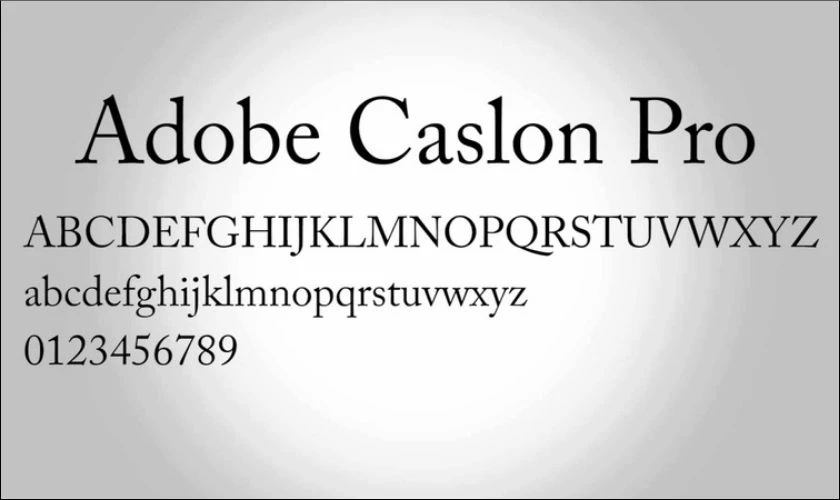
Font chữ La Mã (Roman Capitals) là nhóm phông chữ có chân (Serif) mang tính biểu tượng lịch sử lâu đời nhất trong nghệ thuật Typography, được lấy cảm hứng từ các bản khắc chữ trên đài kỷ niệm và bia đá của Đế chế La Mã cổ đại. Với cấu trúc chữ in hoa uy nghi, các chân chữ sắc sảo và tỷ lệ kiến trúc chuẩn mực, nhóm phông chữ này toát lên vẻ đẹp quyền lực, trang trọng và trường tồn với thời gian. Doozypack.vn cung cấp link tải trọn bộ font chữ La Mã đẹp đã được Việt hóa chuẩn kỹ thuật, giúp bạn sở hữu kho phông chữ cổ điển này để thiết kế bao bì, nhãn rượu và bộ nhận diện thương hiệu cao cấp mà không lo lỗi hiển thị dấu thanh.
Đặc điểm thẩm mỹ độc đáo của bộ font chữ La Mã
Font chữ La Mã không chạy theo các xu hướng thiết kế nhất thời; sức hút của nó nằm ở sự chuẩn xác mang tính toán học và tinh thần monumental (hoành tráng, uy nghi) của kiến trúc cổ đại.
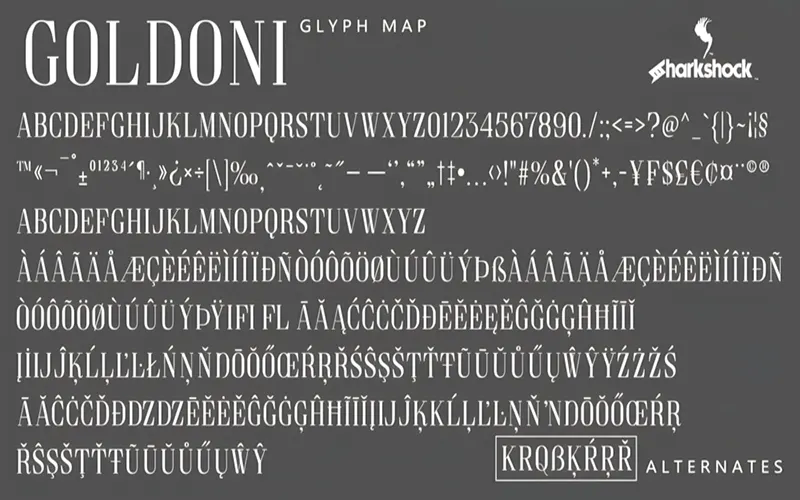
Phong cách Roman Capitals uy nghi mang âm hưởng đế chế cổ đại
Đặc trưng lớn nhất của phông chữ La Mã là hệ thống ký tự in hoa (All-caps) với tỷ lệ chiều rộng và chiều cao được tính toán dựa trên các hình khối hình học chuẩn mực. Các nét dọc sở hữu độ dày đĩnh đạc kết hợp cùng các nét ngang thanh thoát, tạo nên cảm giác vững chãi, uy quyền và minh bạch tuyệt đối. Khi đặt font La Mã làm tiêu đề trên bao bì, thương hiệu của bạn sẽ ngay lập tức khẳng định được vị thế di sản, sự uy tín lâu năm và phẩm cấp thượng hạng.
Chân chữ sắc sảo với tỷ lệ kiến trúc chuẩn mực
Phần chân chữ (serif) của kiểu chữ La Mã được thiết kế rất sắc lẹm, có độ mở rộng vừa phải ở các điểm kết thúc nét. Chi tiết điêu khắc tinh xảo này giúp các dòng tiêu đề trên vỏ hộp giữ được sự thanh thoát, kiêu kỳ nhưng vẫn vô cùng chắc chắn, rất phù hợp với các sản phẩm quà tặng doanh nhân, hộp rượu vang lâu năm hoặc văn bằng chứng nhận cao cấp.
Các biến thể phổ biến: Từ chữ cái đến Font chữ số La Mã
Khi tìm kiếm các bộ phông chữ này, bạn sẽ bắt gặp hai nhóm ứng dụng chính rất được ưa chuộng trong thiết kế đồ họa:
- Font chữ số La Mã đẹp (Roman Numerals): Các ký tự số như I, II, III, IV, V, X, L, C, M được thiết kế theo đúng chuẩn kiến trúc La Mã, thường được dùng để đánh dấu các phiên bản giới hạn (Limited Edition), mốc thời gian thành lập công ty hoặc số thứ tự tập sách.
- Font chữ La Mã toàn bộ (Full Family): Bao gồm cả chữ cái và số, hỗ trợ tối đa cho việc dàn trang các tiêu đề lớn, bìa sách nghệ thuật hoặc nhãn dán sản phẩm cao cấp cần sự trang trọng.